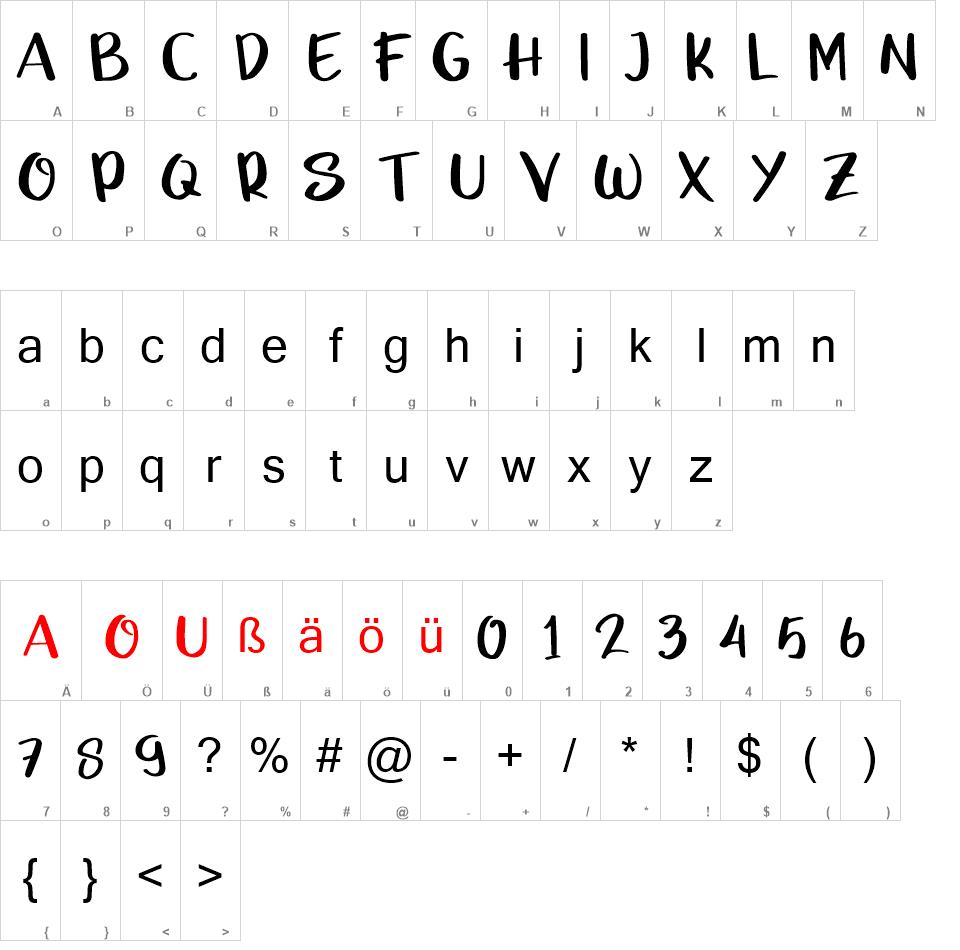
Ucu Aned
Hallo! Ucu Aned ist eine Fancy Handwriting Font-Schriftart und eine süße Schriftart. Es ermöglicht Ihnen, schöne handgemachte Typografie im Handumdrehen zu erstellen.
Ucu Aned ist Anzug für jede Art von Design wie Branding-Projekte, Logo, Hochzeit Designs, Social Media Beiträge, Werbung, Produktverpackungen, Produktdesigns, Etiketten, Fotografie, Wasserzeichen, Einladung, Poster, T-Shirt-Design, Schreibwaren und alle Projekte, die Handschrift Geschmack brauchen.